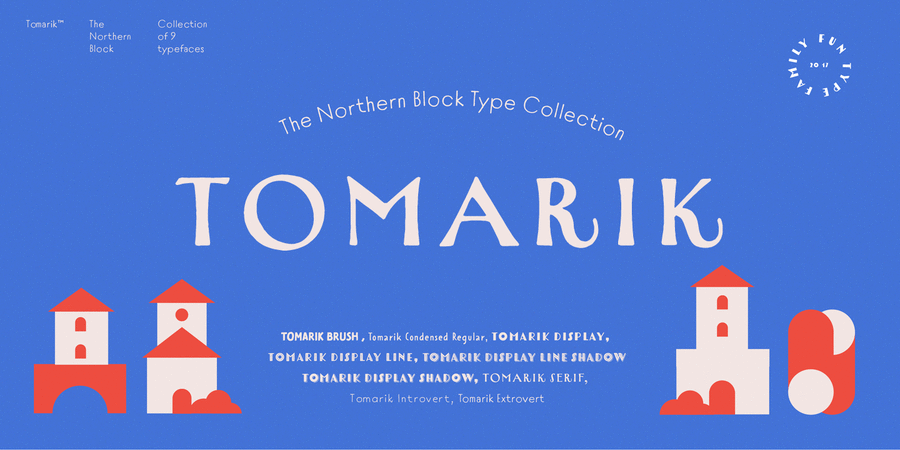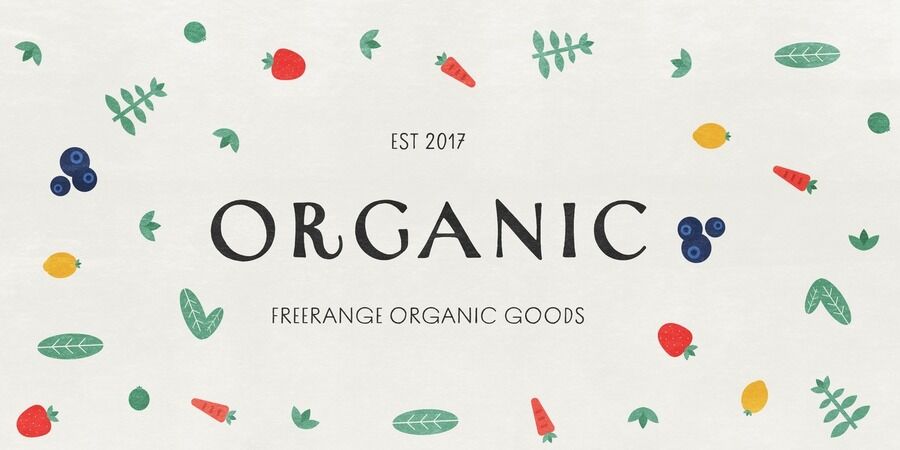
Чудернацька антиква, намальована вручну – частина яскравої колекції рукописних шрифтів Томарік. Грайливе доповнення будь-якого творчого проекту. Шрифтової набір, зібраний для роботи за принципом «обирай і змішуй», він пропонує велику різноманітність стилів і характерів. Томарік містить дев'ять різних накреслень з латинкою та кирилицею і включає функції OpenType, такі як верхні та нижні індекси і дроби. Шрифт розробила Марія Пігулевська у 2017 році. Tomarik™ є торговою маркою компанії The Northern Block.
Асоціації з сімейством шрифтів Tomarik SerifОсобистість і характер гарнітури:
цікавий, характерний, манірний, химерний, чудний, оригінальний, старомодний, старовинний, історичний, іронічний, благородний, красивий, виразний, пафосний, урочистий, амбітний, художній, римський, крафтовий, динамічний, фантастичний, імперський, казковий, видовищний, величний, кінематографічний, монументальний, архітектурний, гуманітарний, джентльменський, святковий, аристократичний, гордий, ефектний, модний, багатий, претензійний, салонний, сексуальний, романтичний, яскравий, привабливий, екстравагантний, естетський, театральний, пристрасний, гарненький, симпатичний, золотий, органічний
мода, перукарня, косметика, парфумерія, краса, одяг, бутік, Модель, салон, туфлі, каблук, театр, романтика, кава, Інстаграм, ювелір, готель, геральдика, свято, скульптура, історія, кіно, видовище, тату, татуювання, вино, архітектура, Трофей, нагорода, література, прикраса, мистецтво, пригоди, живопис, Чарівна казка, казка, їжа, ресторан, закуска, розваги, атракціон, гра, карти, антикваріат, чай, монета, годинник, квіти, подарунки, десерт, меню, кафе, цукерки, графіка, ілюстрація, туризм Гарнітура має ознаки стилів: